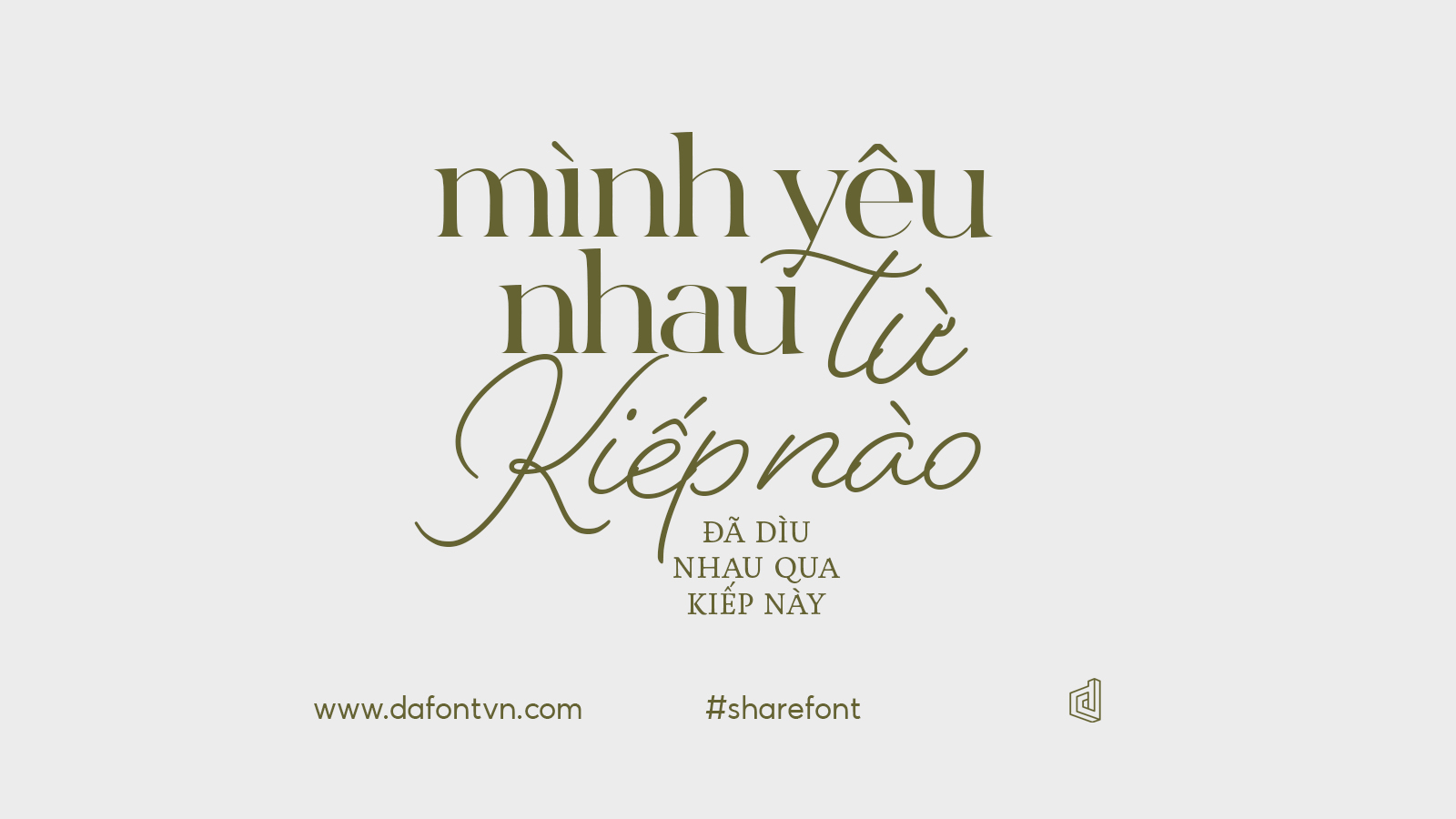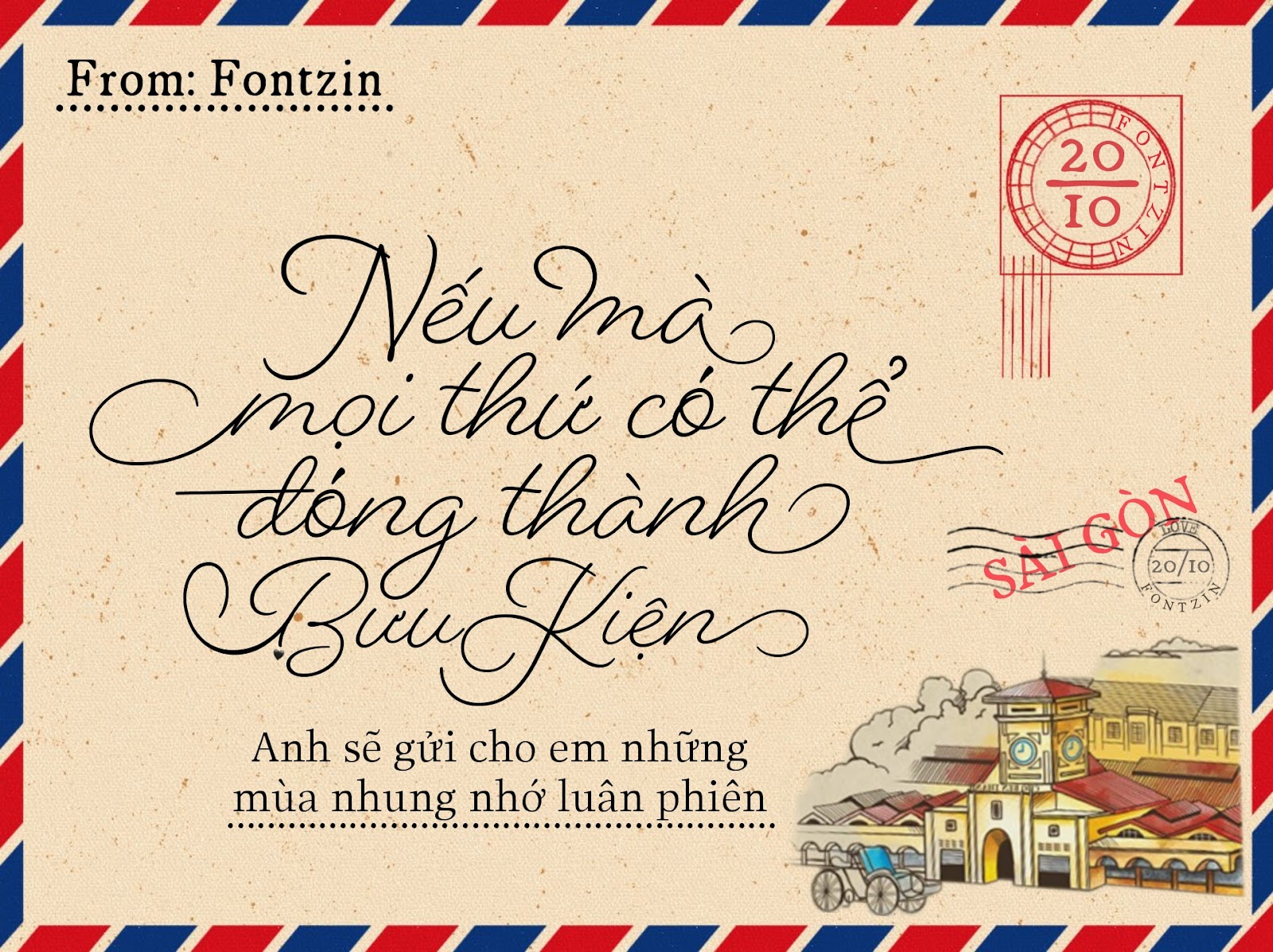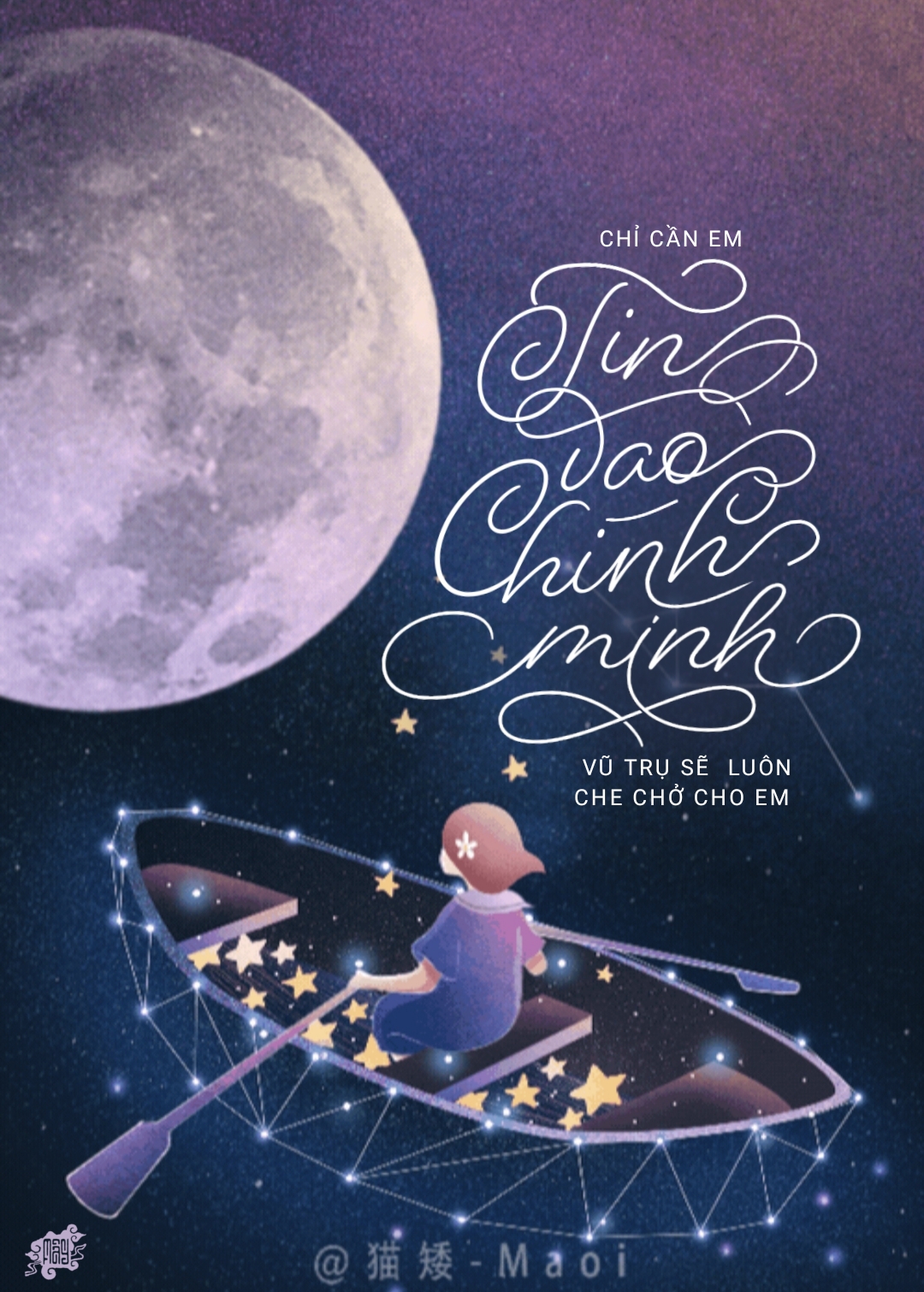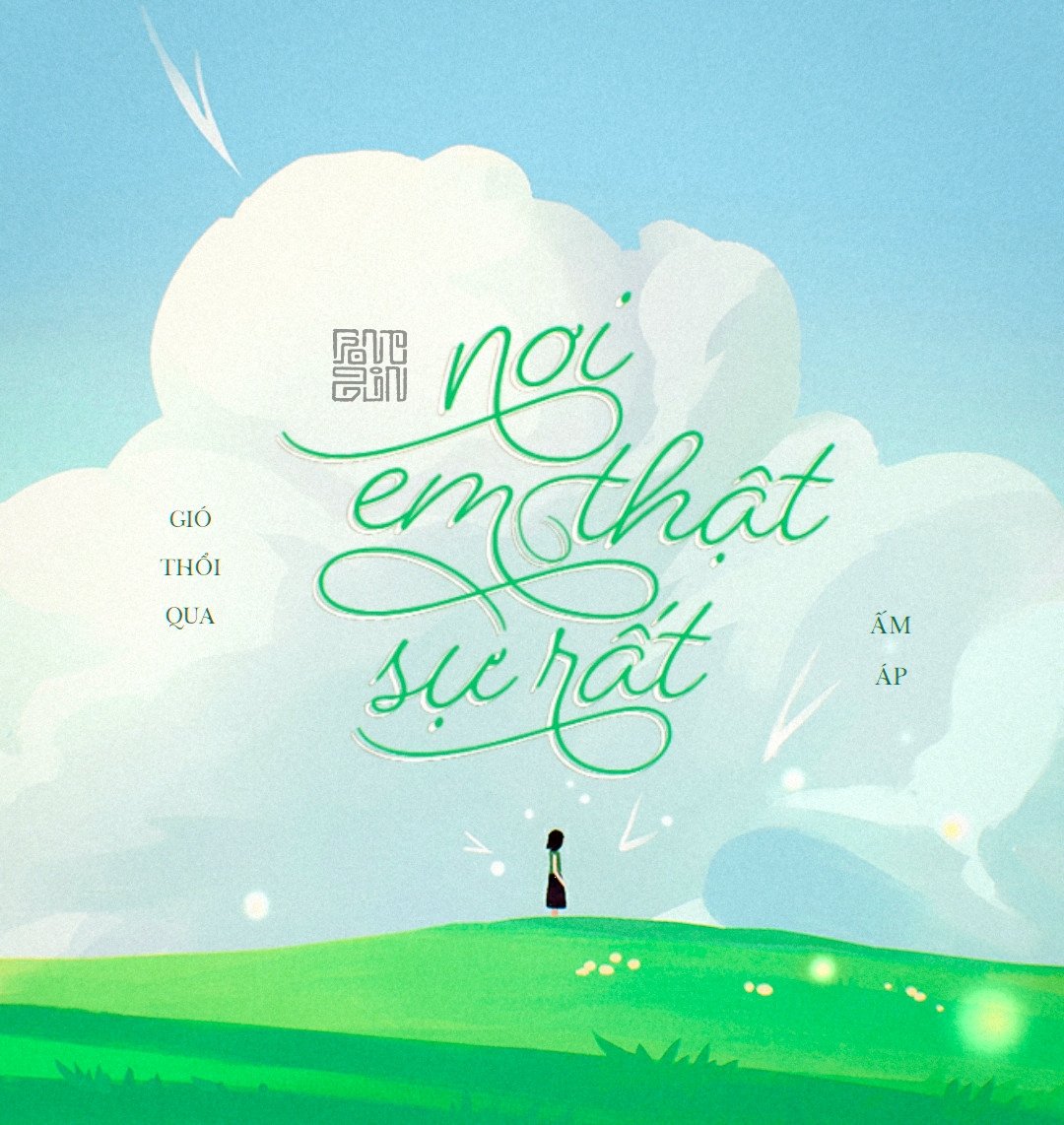
Font Beloved Script Việt Hóa – Font viết tay bút bi
Font Beloved Script Việt Hóa – Font chữ viết tay bút bi. Tác giả đã dựa trên các nét vẽ đơn sắc gợi lên kỹ thuật cầm bút cổ điển của thế kỷ 20 đạt được với các nét chữ bằng bút bi hoặc ngòi bút bi tròn.
Đặc biệt font Beloved Script không giống với các kiểu chữ khác là áp đặt một số quy tắc “on hoặc off” đơn giản về kết nối ký tự, thì font này thể hiện những nét viết tay bình thường và tự nhiên hơn – semi-connected script. Với các ký tự ấn tượng được thay thế bởi hơn 40 chữ ghép.
Beloved Script sống động nhưng mang lại một cảm giác giản dị. Với hơn 1000 dấu gạch chéo và các kiểu thay thế để lựa chọn, bao gồm chữ viết hoa, chữ thường, các nét uốn cong mĩ miều. Font được Việt Hóa bởi FontZin.